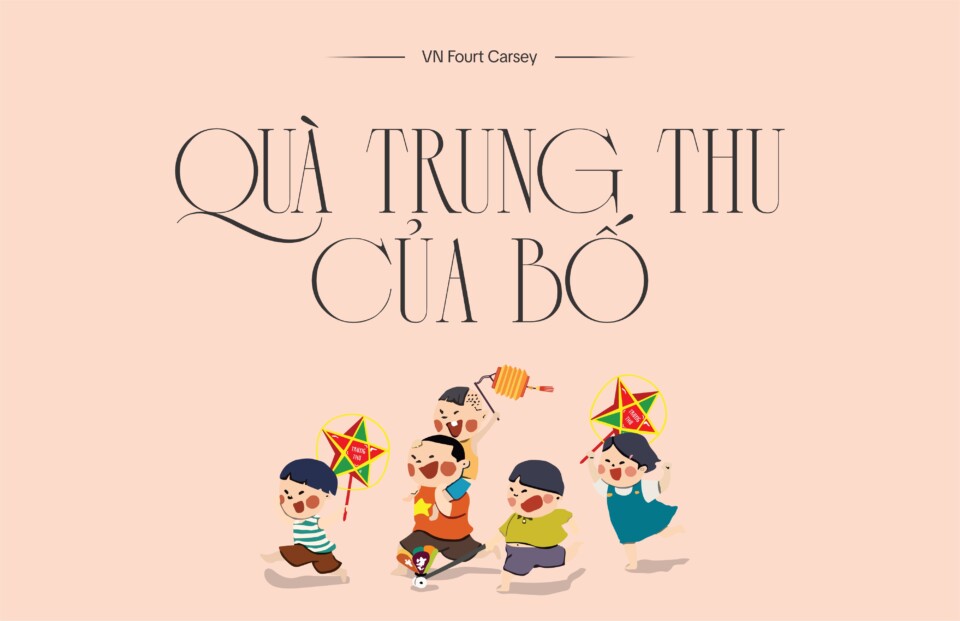
Font Việt hóa VN Fourt Carsey
Giới thiệu về Font Việt hóa VN Fourt Carsey trong thiết kế hiện đại
Trong thế giới thiết kế đồ họa ngày nay việc lựa chọn một bộ Font Miễn Phí chất lượng đóng vai trò vô cùng quan trọng để tạo nên linh hồn cho tác phẩm. Font Việt hóa VN Fourt Carsey nổi lên như một hiện tượng trong cộng đồng designer tại Việt Nam nhờ phong cách Serif cổ điển nhưng không kém phần thanh lịch. Đây là một bộ font chữ mang hơi hướng Victoria tinh tế giúp các bản thiết kế trở nên sang trọng và đẳng cấp hơn bao giờ hết. Được tinh chỉnh tỉ mỉ để phù hợp với bảng mã tiếng Việt bộ font này đảm bảo không xảy ra lỗi hiển thị dấu khi soạn thảo văn bản trên các phần mềm đồ họa phổ biến. Sự kết hợp giữa những đường nét mảnh dẻ và các góc cạnh bo tròn nhẹ nhàng làm cho VN Fourt Carsey trở thành lựa chọn ưu tiên cho các dự án yêu cầu tính thẩm mỹ cao và sự chuyên nghiệp tuyệt đối trong từng con chữ.
Những đặc điểm nổi bật của Font Việt hóa VN Fourt Carsey
Phong cách thiết kế Serif độc đáo và ấn tượng
Đặc trưng lớn nhất của Font Việt hóa VN Fourt Carsey chính là sự cân bằng hoàn hảo giữa nét cổ điển và hơi thở đương đại. Các chân chữ được thiết kế rõ ràng giúp định hình cấu trúc văn bản một cách mạch lạc hỗ trợ người xem dễ dàng tiếp nhận thông tin mà không bị mỏi mắt. Font chữ này mang lại cảm giác hoài cổ về những trang sách quý hay các biển hiệu nghệ thuật xưa cũ nhưng vẫn đủ linh hoạt để ứng dụng vào các website thời trang cao cấp. Mỗi ký tự trong bộ font đều được trau chuốt để giữ được sự đồng nhất về khoảng cách tạo nên một tổng thể hài hòa khi đứng cạnh nhau.
Khả năng ứng dụng đa dạng trong nhiều lĩnh vực
Không chỉ dừng lại ở việc trình bày văn bản thông thường Font Việt hóa VN Fourt Carsey còn là “vũ khí” đắc lực cho việc thiết kế logo nhận diện thương hiệu. Bạn có thể sử dụng font này để thiết kế bìa sách thiệp mời đám cưới thực đơn nhà hàng sang trọng hay các poster quảng cáo sự kiện văn hóa. Với bộ ký tự tiếng Việt đầy đủ bạn hoàn toàn yên tâm khi thực hiện các dự án nội địa mà không lo bị mất đi vẻ đẹp nguyên bản của font chữ gốc. Đối với các bạn học sinh và giáo viên đây cũng là công cụ tuyệt vời để trang trí bài thuyết trình Powerpoint thêm phần lôi cuốn và khác biệt so với các font hệ thống thông thường.
Kết luận về giá trị của bộ font đối với người dùng